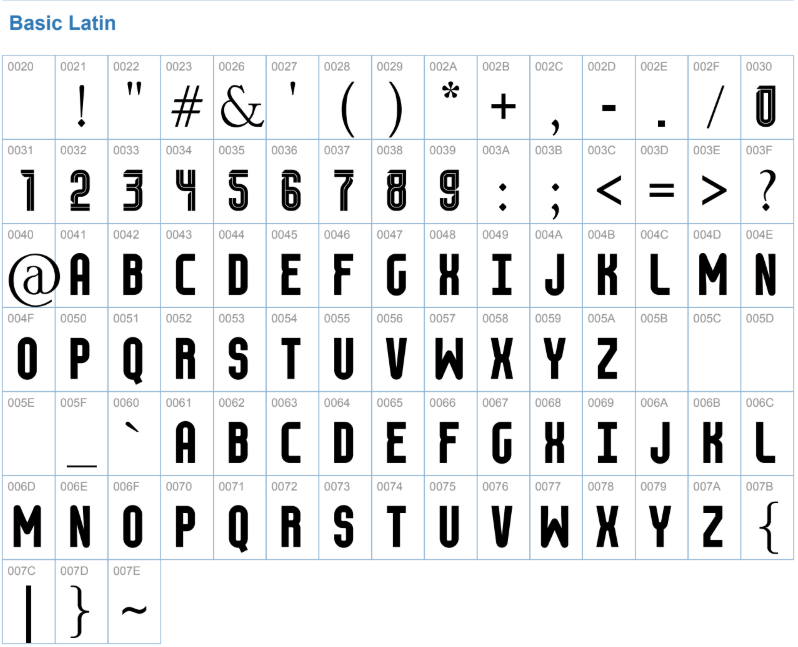
O Flamengo entra em 2026 com peso de camisa e modernidade gráfica. A cada temporada, a identidade visual do clube avança sem perder a tradição que move a Nação. Um dos elementos que mais chamam atenção de designers e torcedores é a tipografia estampada no manto.
A fonte oficial funciona como extensão da marca CRF. Ela comunica força, velocidade e pertencimento. Para quem trabalha com design, produz camisas personalizadas ou cria conteúdo nas redes, ter acesso a esse arquivo virou prioridade absoluta antes mesmo da bola rolar.
Estilo visual da tipografia
Os números de camisa trazem recortes geométricos agressivos, com ângulos que remetem à velocidade das jogadas pelas pontas. As hastes são grossas e estáveis, garantindo leitura imediata tanto no estádio quanto na transmissão em 4K.
A direção de arte do clube manteve a alma raçuda do rubro-negro, mas aplicou refinamento nos contornos. O resultado é uma fonte que respira tradição com toque europeu de finalização.
Aplicação no uniforme
No manto titular, a tipografia aparece em branco com contorno preto fino, garantindo máximo contraste sobre as listras horizontais. A versão away aplica a fonte em vermelho sólido sobre base clara. Já o terceiro uniforme trabalha com acabamento metálico em dourado.